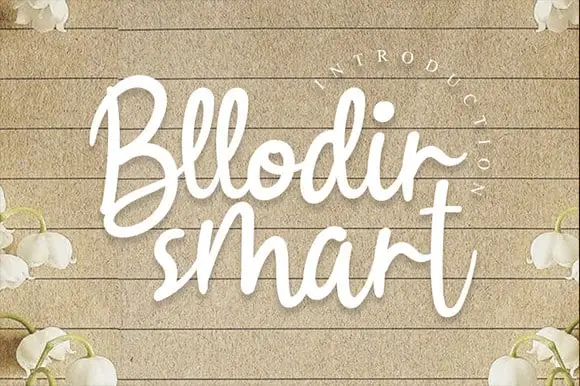
A Bllodir Smart Script Font é uma escolha perfeita para designers que buscam adicionar um toque especial a seus projetos. Esta nova tendência em letras serifadas traz sofisticação e modernidade, ideal para diversas aplicações como displays de parede, convites de casamento, logotipos para posts nas redes sociais, anúncios, embalagens de produtos, designs de produtos, rótulos, fotografia e até mesmo marcas. Ela é perfeita para qualquer projeto que deseje um visual elegante e autêntico, seja em uma pequena etiqueta ou um banner em tamanho grande. Com o designer andikastudio, a Bllodir Smart Script Font oferece aos criadores de conteúdo a oportunidade de criar experiências de marca memoráveis. A fonte é versátil, proporcionando aos designers flexibilidade para adaptar seu design à sua necessidade específica. Que seja para uma breve anúncio digital ou um lindo convite de casamento que exige cuidado e detalhes, a Bllodir Smart Script Font traz a elegância que se espera de uma fonte de escrita artística. Para designers mais avançados, a Bllodir Smart Script Font não apenas enriquece o visual do seu trabalho, mas também pode ser usada para personalizar layouts complexos com facilidade. Essa fonte é uma maneira conveniente e sofisticada de incorporar um estilo único em seus projetos, garantindo que cada peça seja única e memorável. Com a Bllodir Smart Script Font, você não precisa apenas adicionar um design à sua coleção – transforma-a para algo extraordinário.